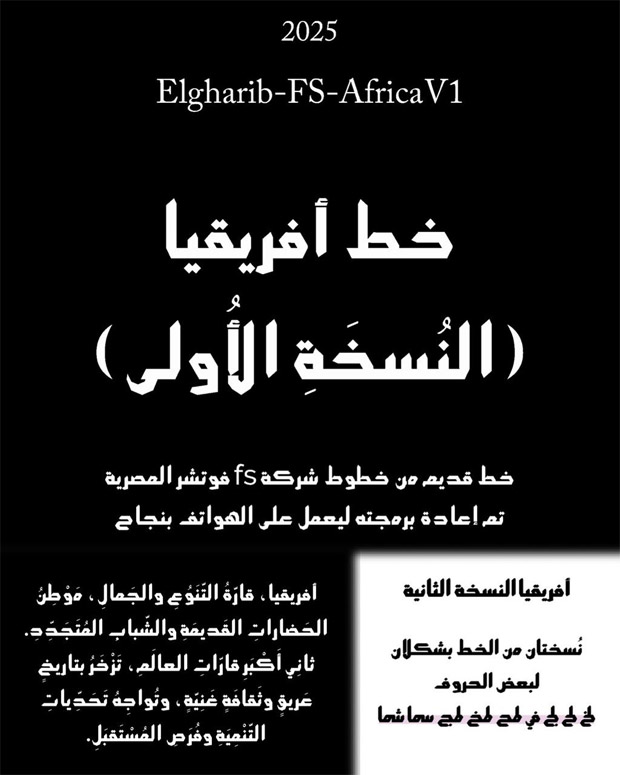
خط أفريقيا الهندسي للحاسب والموبايل .. الخط يحوي تشكيل بدائي كامل ورموز خاصة للخط، ولاتيني عام، وهناك نسخة ثانية لبعض الحروف المستبدلة، وهو متاح للتحميل المجاني الآن.
خط أفريقيا الهندسي للحاسب والموبايل